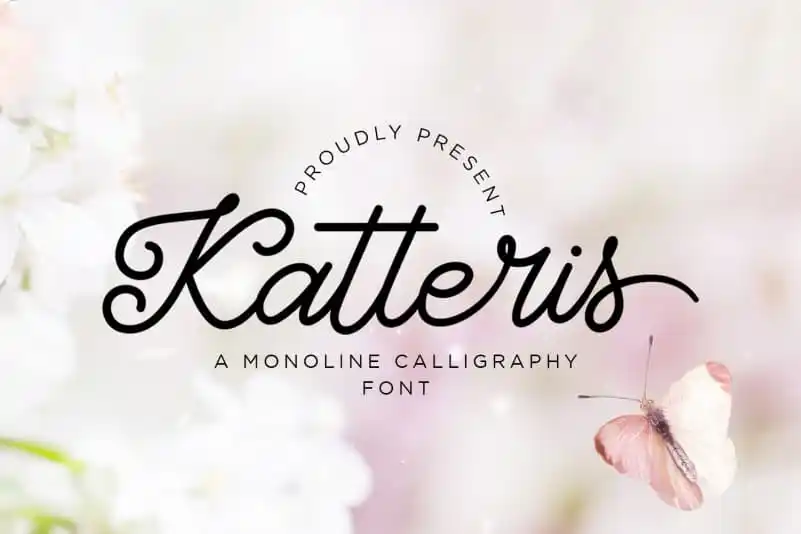
Katteris – Monoline Calligraphy Font – Fonte Grátis
Katteris - Monoline Calligraphy Font
Katteris – Monoline Calligraphy Font é uma bela fonte de calligrafia monolínea com um estilo autêntico e casual, perfeitamente adaptada para uma variedade de projetos visuais. Esta fonte exalta a sofisticação da calligrafia tradicional enquanto mantém uma leveza e naturalidade que tornam seu uso não apenas elegante, mas também acessível. Apropriada tanto para criações branding como para design de logotipo, esta fonte se destaca no mundo dos materiais de embalagem ou embutida em camisas de shopping bag. Ela é um recurso inestimável para designers de moda e gráficos que desejam dar um toque especial a suas criações visuais. Seja em sua capa de livro, na sua página web ou no seu site, Katteris – Monoline Calligraphy Font traz uma personalidade única à cada projeto. Suas linhas finas e detalhes meticulosos complementam qualquer projeto gráfico, garantindo que ela se destaque entre as demais. A fonte de calligrafia monolínea é uma escolha perfeita para designer de publicações ou editoriais de revistas. Sua versatilidade permite aplicação em um grande número de formatos e tipos de materiais, tornando-a uma opção indispensável para qualquer designer gráfico. Seja qual for seu projeto, Katteris – Monoline Calligraphy Font oferece a perfeita combinação de estilo elegante e confiabilidade casual.
Designer: Naharstd